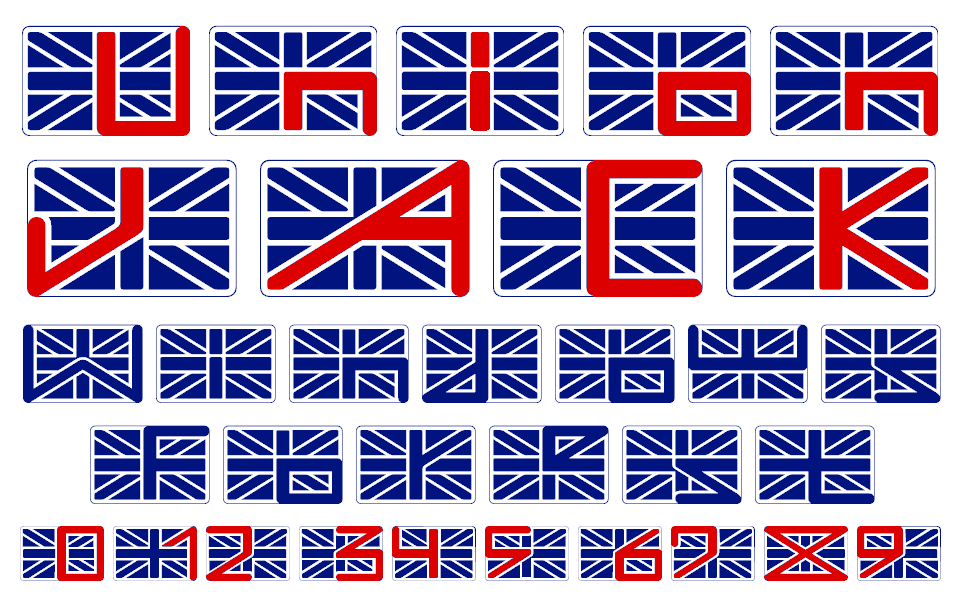
イギリス国旗の十字模様で英数字を表現した無償フォント「Union Jack」
16セグメントディスプレイのように見立てたデザイン
ユニオン・ジャックとも呼ばれるイギリス国旗、正確に言えばグレートブリテン及び北アイルランド連合王国の国旗は、その構成国であるイングランドとスコットランドの国旗に、聖パトリックのシンボルを合成したもの。直線で構成された非対称な模様と配色は、イギリス文化の象徴としてデザインに取り入れられることも多い。
EUからの離脱でも注目を集める、そんなイギリス国旗をフォント化した「Union Jack」は英数字と一部の記号を収録し、十字模様の区切り方で各文字を表現している。その発想は16セグメントディスプレイのようだ。
単色の印字でも読めないことはないが、そもそもイギリス国旗であることが少しわかりにくい。やはり、文字の部分を強調するためにも、そのデザイン性を引き立てるためにも赤と青で塗り分けたほうがよいだろう。
作者の秘話によれば、ロンドンで個展を開いた時、現地の人にも理解できるデザインとして制作したという。しかし、このイギリス国旗でギャラリーを飾ったところ、ナショナリストの集会に勘違いされてしまったのだとか。